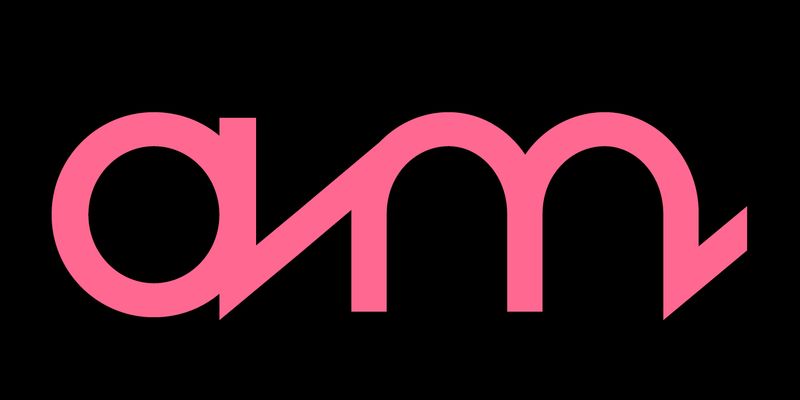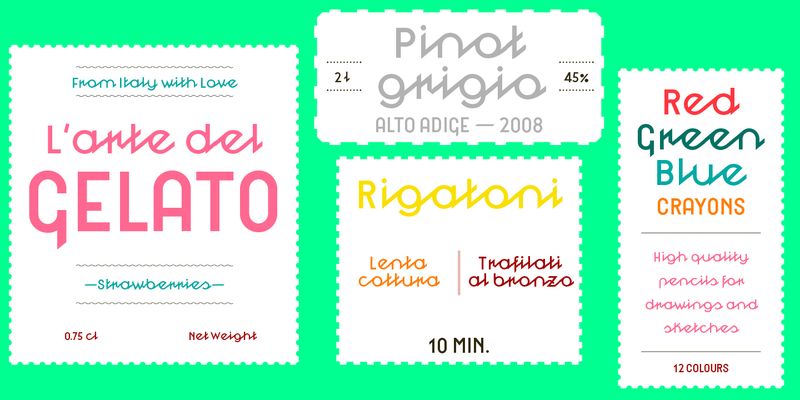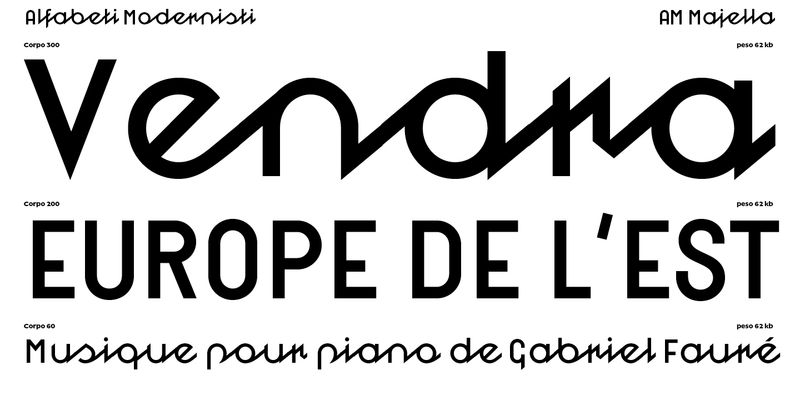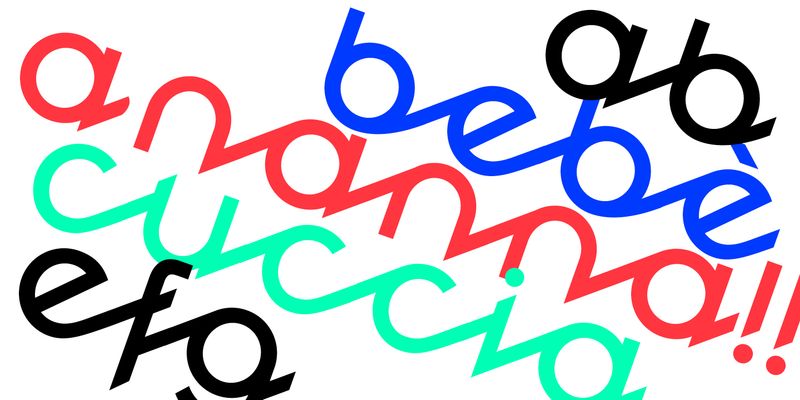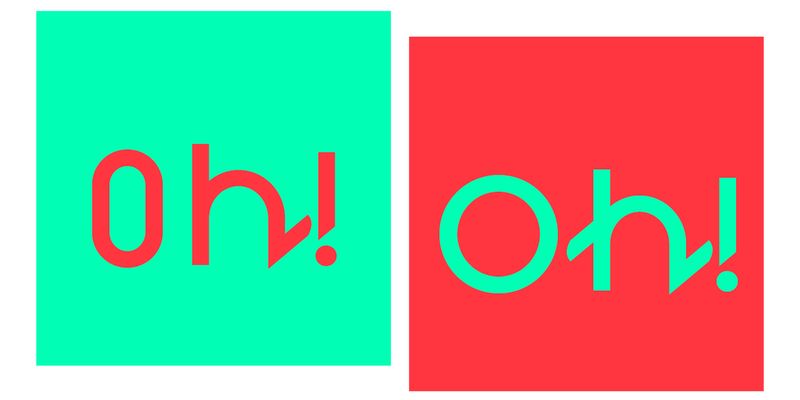
Majella는 기하학적 디자인이 강력하고, x 높이가 크고, 두껍고 얇은 대비가 없는 소문자 전용 결합 스크립트 서체입니다. 필기체와 기하학적 산세리프체가 ‘상당히’ 뒤섞여 있습니다. 원 기반의 비율과 거의 45°의 들어가는 획과 나가는 획으로 합리적인 디자인이 가미되고 일반적인 차원에서 움직임과 역동성이 부여됩니다.
중부 아펜니노(이탈리아) 산맥에서 이름을 따온 Majella는 1937년과 1939년 사이에 Xilografia di Verona에서 세 가지 크기(라인 3, 4 및 5개 또는 포인트 36, 48 및 60개)로 출시한 목활자입니다. Volturno 이름의 동일한 디자인은 Xilografia Italiana의 1941년 카탈로그에 등장합니다. 1930년대이 글자 형태가 크게 유행했다는 증거는 1937년 이탈리아 출신 유명 등반가 겸 기업가인 Vitale Bramanti가 디자인하고 출시한 최초의 등산용 고무 밑창인 Carrarmato(영어로 ‘탱크’)의 Vibram 로고에서 찾아볼 수 있습니다.
AM Majella 디지털 부활은 오리지널 소문자 디자인을 그대로 유지하면서 대문자 세트를 새로 추가하고 있습니다. 이는 구두점과 함께 오리지널 문자 세트의 일부였던 그림 디자인을 기반으로 합니다. 모듈식 구조를 따르지만 그림과 대문자는 소문자에 비해 폭이 매우 좁습니다. 그림과 대문자는 덕트와 무관하고, 상호 또는 소문자와 연결되지 않습니다. 또한 AM Majella 디자이너 Valentina Casali는 ‘소문자 중 일부가 기울어져 있거나 부드럽게 연결되지 않아서’ 연결을 원활하게 만들었습니다.
AM Majella는 OpenType 기능을 통해서 오리지널 모델보다 훨씬 더 부드러운 텍스트 구성 환경을 제공합니다. 연결 획 모양은 글자의 위치(초기, 중간, 최종, 고립)에 따라 변경됩니다. Casali는 “시스템을 조작하여 이 기능을 상황별 대체 버전이 아닌 표준 합자에 추가하면 기본적으로 InDesign과 같은 소프트웨어에서 문자를 결합할 수 있습니다”라고 말합니다.
OpenType 기능:
Liga – 위치 대체 버전 활성화: 고립, 초기, 최종
ss01 – 원형 O